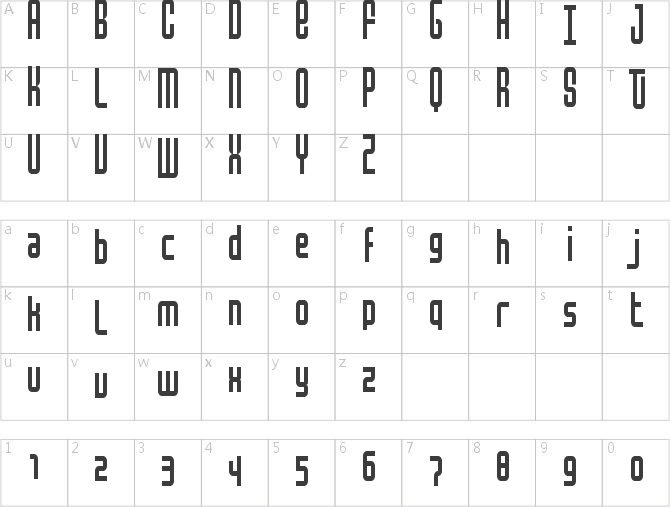
Mocha-Condensed-Regular 詳情頁
字體名稱: Mocha-C
Mocha-Condensed-Regular
Mocha-Condensed-Regular字體字庫是一款讓人賞心悅目、百看不厭的英文字體,適合各類廣告和產品包裝設計應用,字體大小0.04MB,格式為ttf字體,上傳用戶是rose,作者/版權方為未知